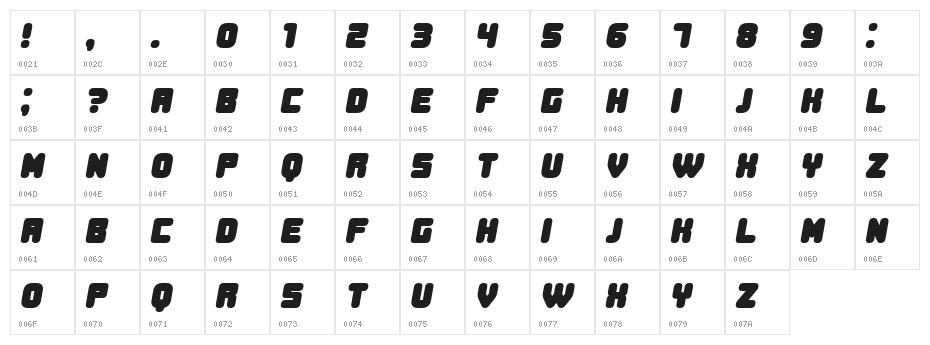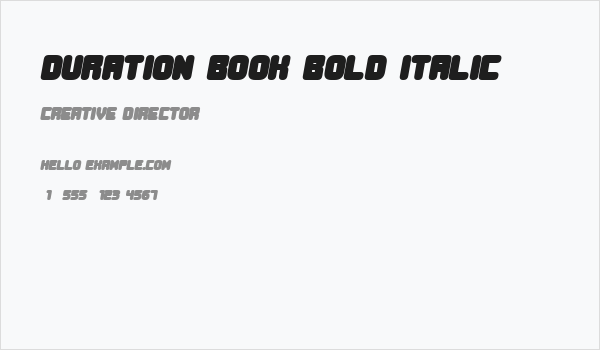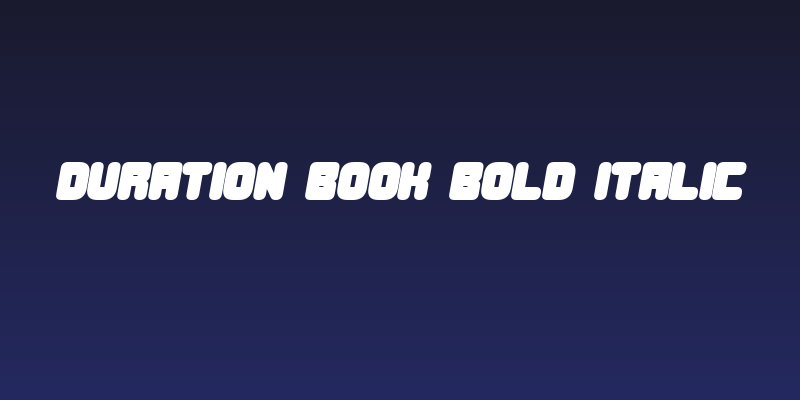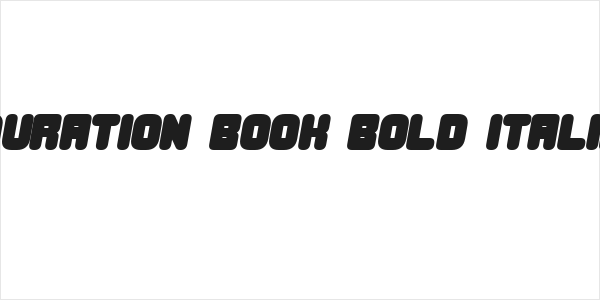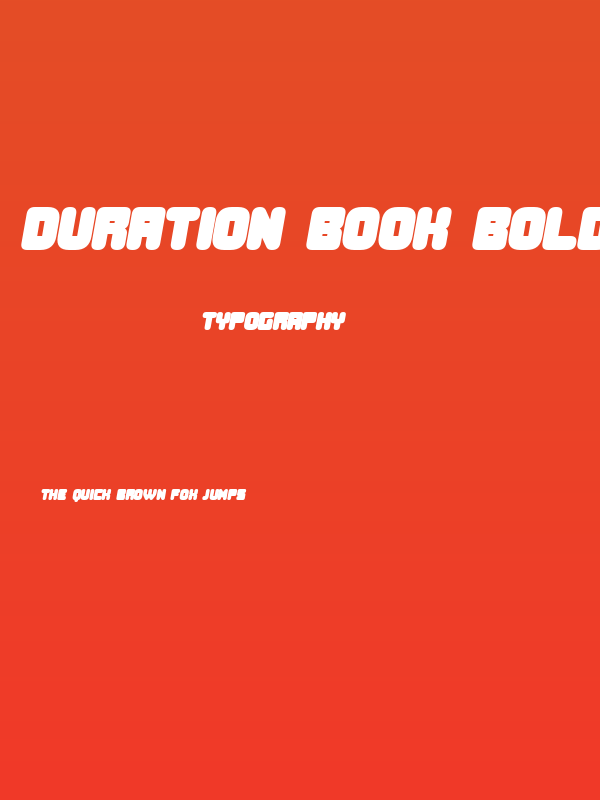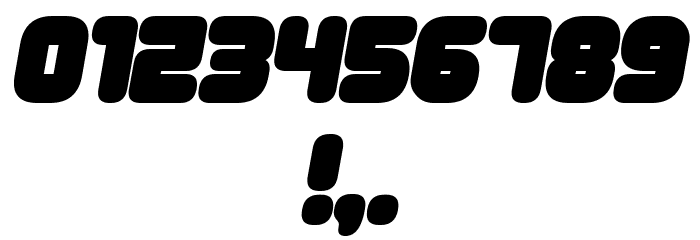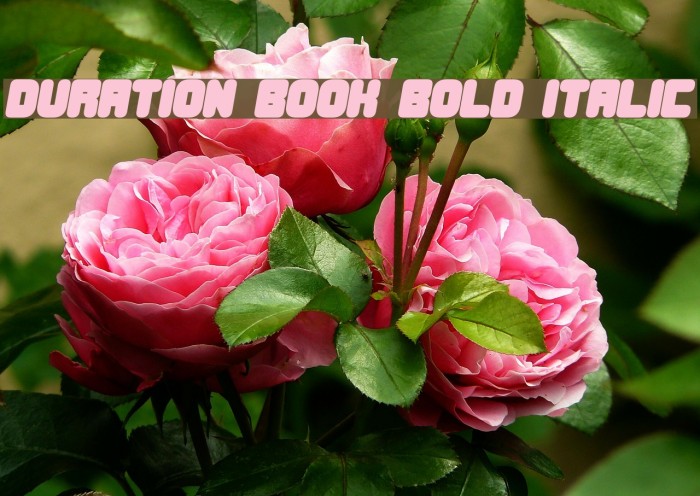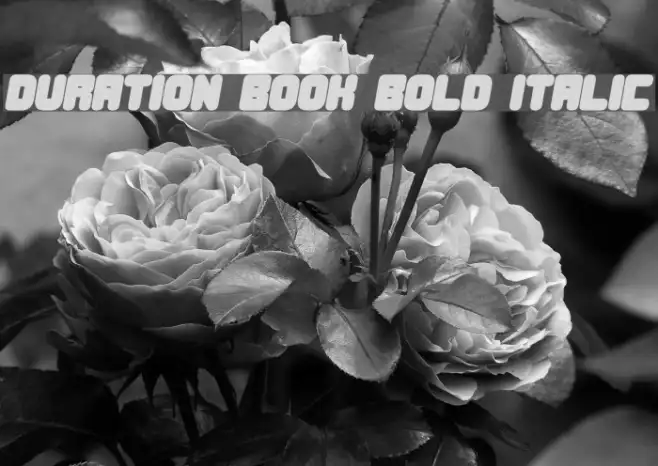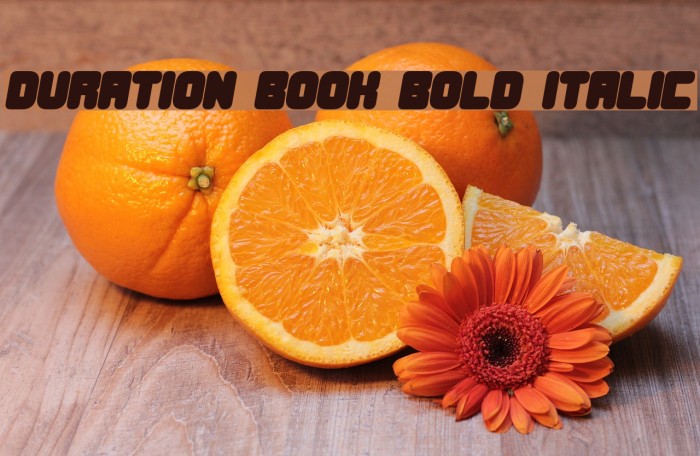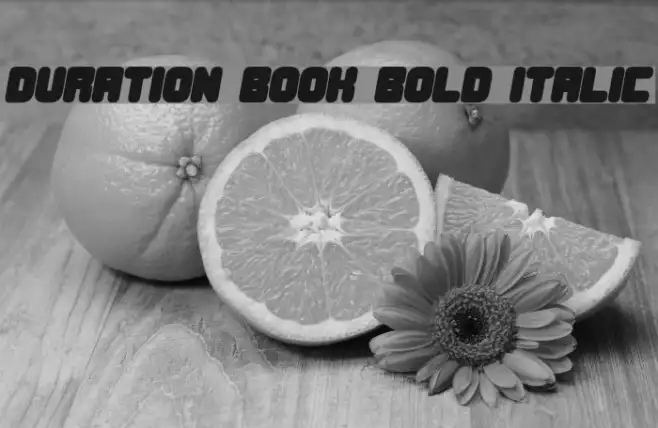
Duration Book Bold Italic Font
✎ Round
| Categorías | Round |
| Caso de uso | Headlines, Logos, Branding |
| Proyectos propuestos | Ideal for branding, advertising, headlines, and packaging design where a bold and approachable look is desired. |